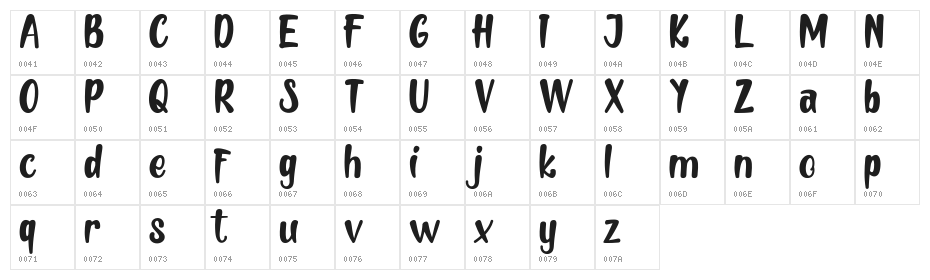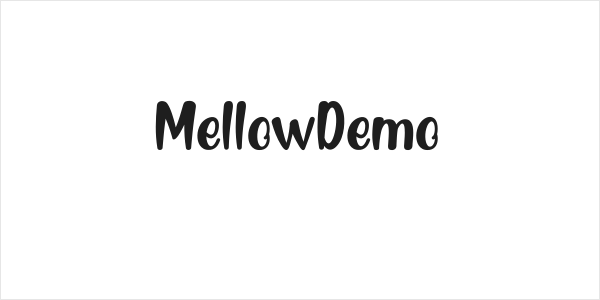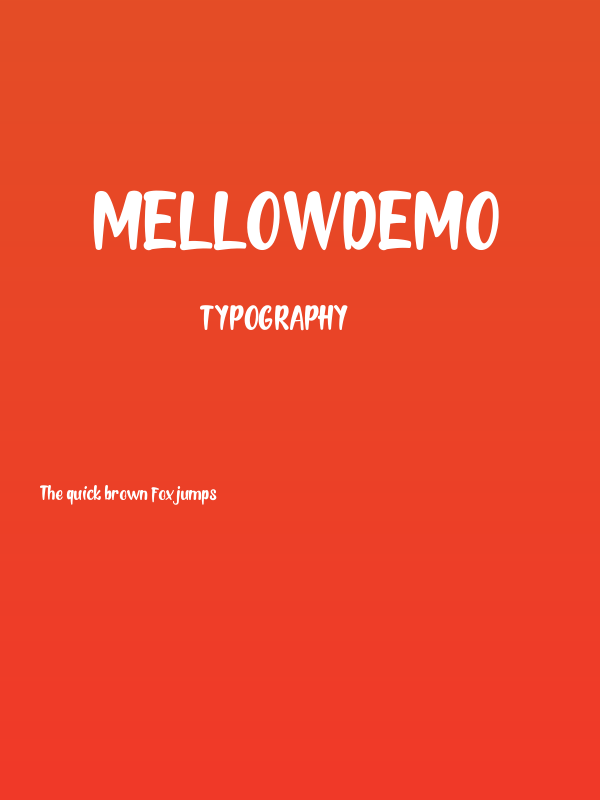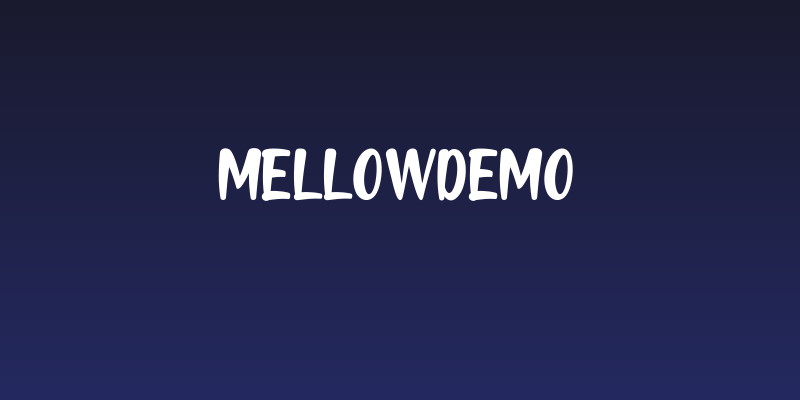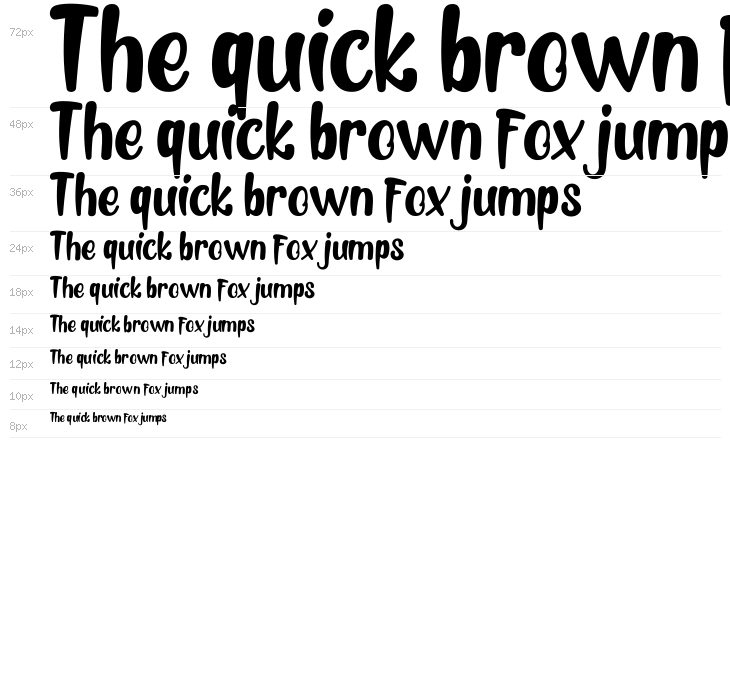
MellowDemo Font
✎ Comic
| Stile generale | Playful, Casual |
| Caso d'uso | Headlines, Logos, Invitations |
| Progetti proposti | Ideal for invitations, greeting cards, playful branding, and artistic projects. |